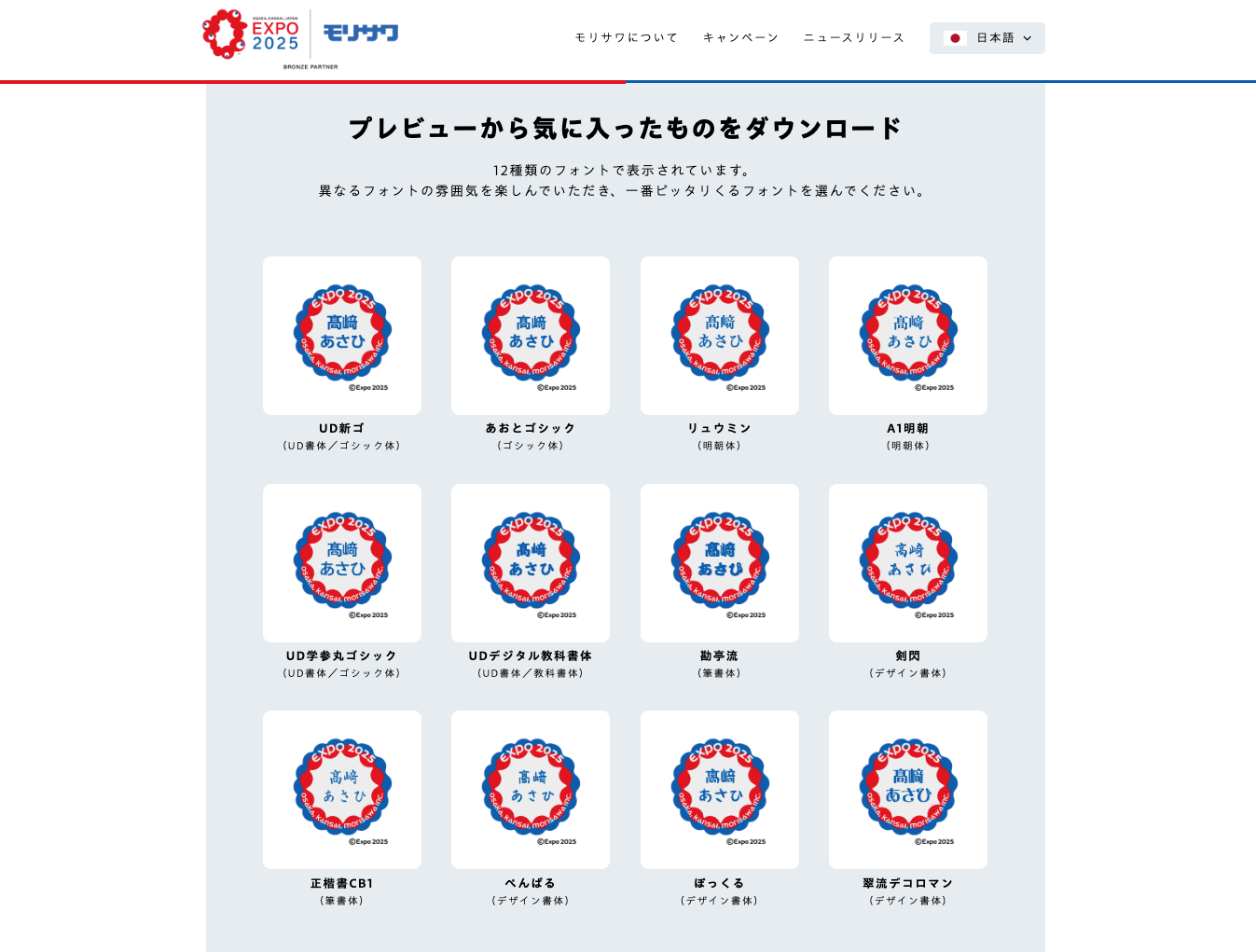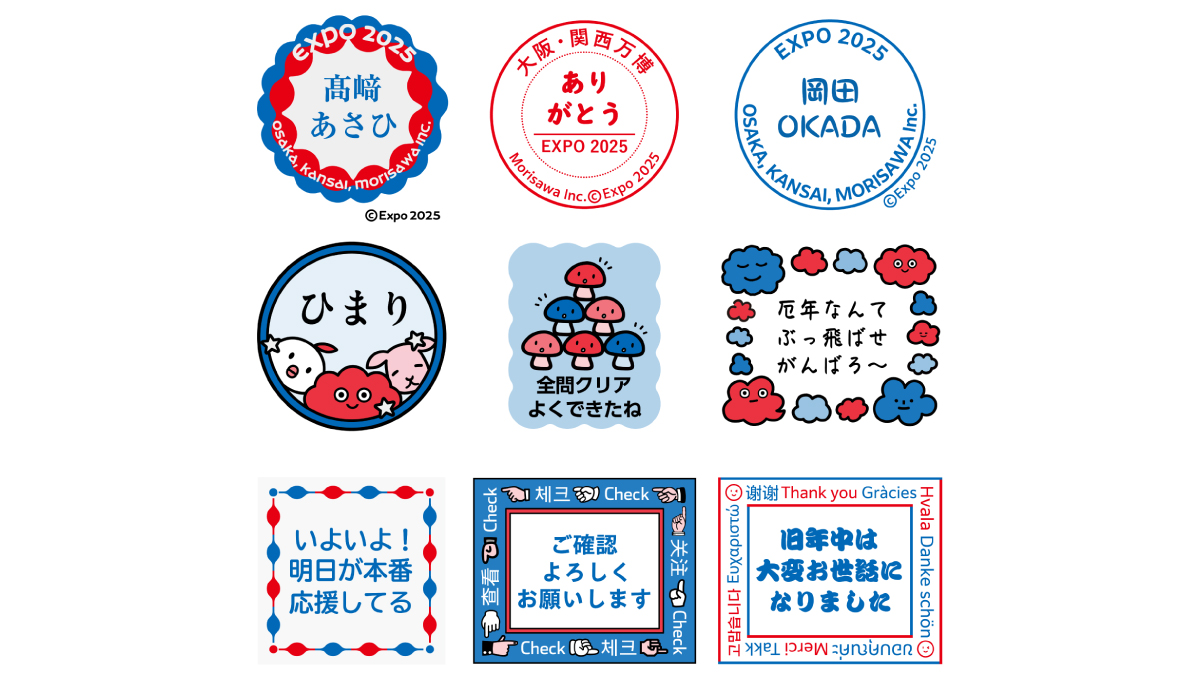
大阪・関西万博記念、好きな言葉&デザイン&フォントでデジタルスタンプが作れる特設サイト「フォント de スタンプ」公開!ミャクミャクデザインのハンコが当たるキャンペーンも同時開催
フォントを選んで作れる!「フォント de スタンプ」は、大阪・関西万博モチーフのデザインを含むフレーム(台紙)とモリサワのフォントを使って、ご自身の好きな言葉やお名前を入力したオリジナルデジタルスタンプ(スタンプ形式のデジタル画像)を作成、ダウンロードでき、フォントを変えることで言葉の印象が変わる楽しさを体験いただけます。ダウンロードしたデジタルスタンプは、電子印鑑として使うのはもちろん、SNSのアイコンや写真、メッセージカードに加工するなど自由にご利用いただくことができます。
フォントを選んで作れる!「フォント de スタンプ」のフレーム(台紙)デザインは全部で9種類、期間限定で大阪・関西万博モチーフのデザインを選ぶこともできます。選べる12種類のフォントは、モリサワの代表的なユニバーサルデザイン(UD)フォントで、大阪・関西万博の会場サインなどに協賛で提供している「UD新ゴ」や、推し活うちわの文字などで人気の高い「勘亭流」、ビジネスシーンでも使用頻度の高い「正楷書CB1」、教育現場でも注目されている「UDデジタル教科書体」や「UD学参丸ゴシック」、近年人気の手書き風フォント「ぺんぱる」などで、自分にぴったりのオリジナルデジタルスタンプを作成することができます。
「フォントの世界へようこそ クイズで学び、スタンプで遊ぼう」と題して、文字の力で大阪・関西万博を盛り上げる特設サイトです。フォントを選んで作れる!「フォント de スタンプ」のほか今後は、クイズ王伊沢拓司氏が率いる知的エンタメ集団「QuizKnock」とコラボレーションしたフォントのクイズも公開予定です。どうぞお楽しみにお待ちください。
モリサワは「大阪・関西万博PRブロンズパートナー」として協賛し、大阪・関西万博の会場サインやアプリなどで使用するための各種フォントも提供しています。また、「大阪ヘルスケアパビリオン Nest for Reborn」のサポーターとして、展示ディスプレイや平面サインなどで使用されるフォントを提供しているほか、その他のパビリオンでも各種フォントを採用いただいています。
モリサワのUDフォントは、「文字のかたちがわかりやすいこと」「文章が読みやすいこと」「読み間違えにくいこと」をコンセプトに開発されています。具体的には、濁点や半濁点を大きくして、区別をつけやすくしているほか、シルエットの似た文字を判別しやすくするために、はなれを明確にするなどの工夫をしています。第三者機関と共同で可視性・可読性に関する比較研究報告も実施しています。